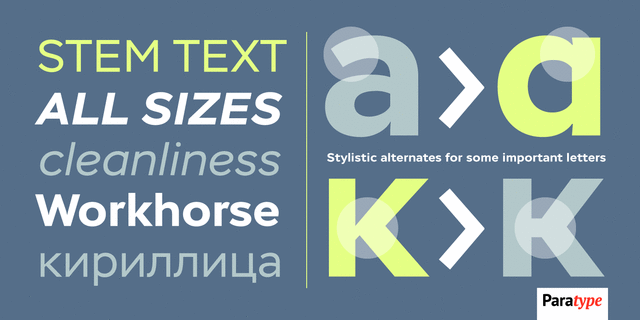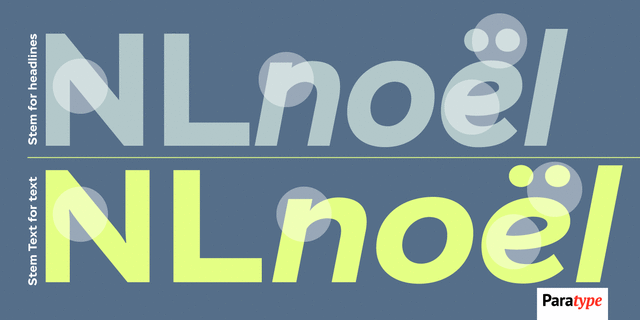
Stem Text (4 шрифта)
Stem Text — шрифт для универсального применения, полузакрытый геометрический гротеск с крупными строчными знаками. Рисунок шрифта позволяет использовать его как в мелких, так и в крупных кеглях. Stem Text полностью совместим с начертаниями гарнитуры Stem и может быть дополнен ими в качестве заголовочных. Дизайн разработан Александрой Корольковой при участии Марии Селезеневой и Изабеллы Чаевой. Выпущен компанией ПараТайп в 2015 году.